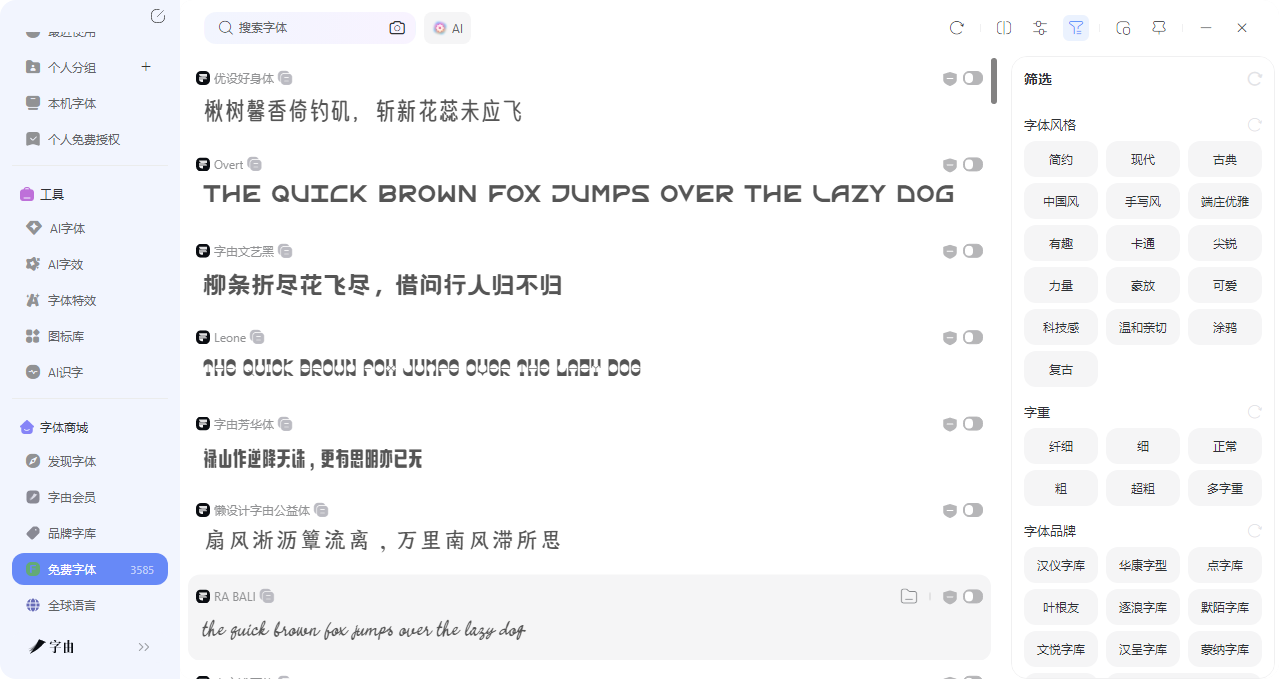
来字由,一键get小红书封面同款字体
小红书的流量密码其实有一半都藏在封面里,如果你是做日常的vlog 的话,灵动、可爱、活泼的字体应用在封面上会很吸睛;如果你是想发制作美食的视频,那么暖色调、有生活气息的字体会比较合适;又或者是你在做美妆博主,那么精致、漂亮的字体会很适配。那么说实在的,小红书不能包揽帖子的全部制作内容,当我们在另外一个平台制作的时候却没有办法使用小红书的字体,那么今天我将教大家如何在一款叫字由的字体平台里寻找小红书封面字体,我会按风格分类推荐一些适合做封面的字体,顺便把筛选方法也交代清楚。想做爆款帖子的朋友,直接收藏这篇。
1、关于字由
我先来讲一下为何要选择字由平台,是因为它收录了超过10500 款字体,其中3584 款是免费可商用的。这个体量意味着什么?就是你看到的大部分小红书封面字体,基本都能在这里翻到。不管是温柔的手写体、大气书法体,还是可爱的艺术字,字由里都有对应的选择。更重要的是,字由支持一键应用到PS、AI、Figma这些软件。你看中哪款字体,不用下载安装,在软件里点一下就能用。试错成本几乎为零——觉得不合适,换下一款接着试。
2、怎么在字由里找到适合的小红书的封面字体?
- 简约:适合极简风、干净利落的封面。
- 现代:适合时尚穿搭、美妆护肤类内容。干货分享这类内容,字体需要干净利落,不抢主体但又有质感,比如说字由文艺黑,既有黑体的稳重,又带一点手写感。用在“穿搭公式”“化妆技巧”“干货总结”上,高级又不死板。
- 古典:适合传统文化、国风类主题。
- 中国风:点进去全是书法体、楷体、隶书这类。这两年国风在小红书上特别火,二十四节气、传统节日、国潮穿搭,配上书法字体,格调瞬间拉高。比如说江西拙楷,带着朴拙手工感的楷书,不刻意追求工整,反而有味道。适合“立春”“中秋”“国风穿搭”这类主题。还有字由颜楷,颜真卿楷书风格,大气稳重。用在“书法”“传统文化”“中式美学”类封面上,压得住场子。
- 手写风:温柔手写、文艺范儿的字体都在这。这种字体在小红书上特别常见,用在情感文案、生活记录、读书笔记类封面上,都十分出效果。比如说字由芳华体,笔画柔和,带着手写的温度。适合“日常 plog ”“治愈系”“我的生活瞬间”这类封面。字体大小适中,排版起来很舒服。
- 端庄优雅:适合婚礼、纪念日、仪式感内容
- 有趣:活泼俏皮的字体,适合探店、美食类。
- 卡通:可爱萌系风格,适合母婴、萌宠。比如说点字婴宝,圆润可爱的风格,比婴宝更活泼一点。用在“美食打卡”“周末去哪儿”上,很有感染力。
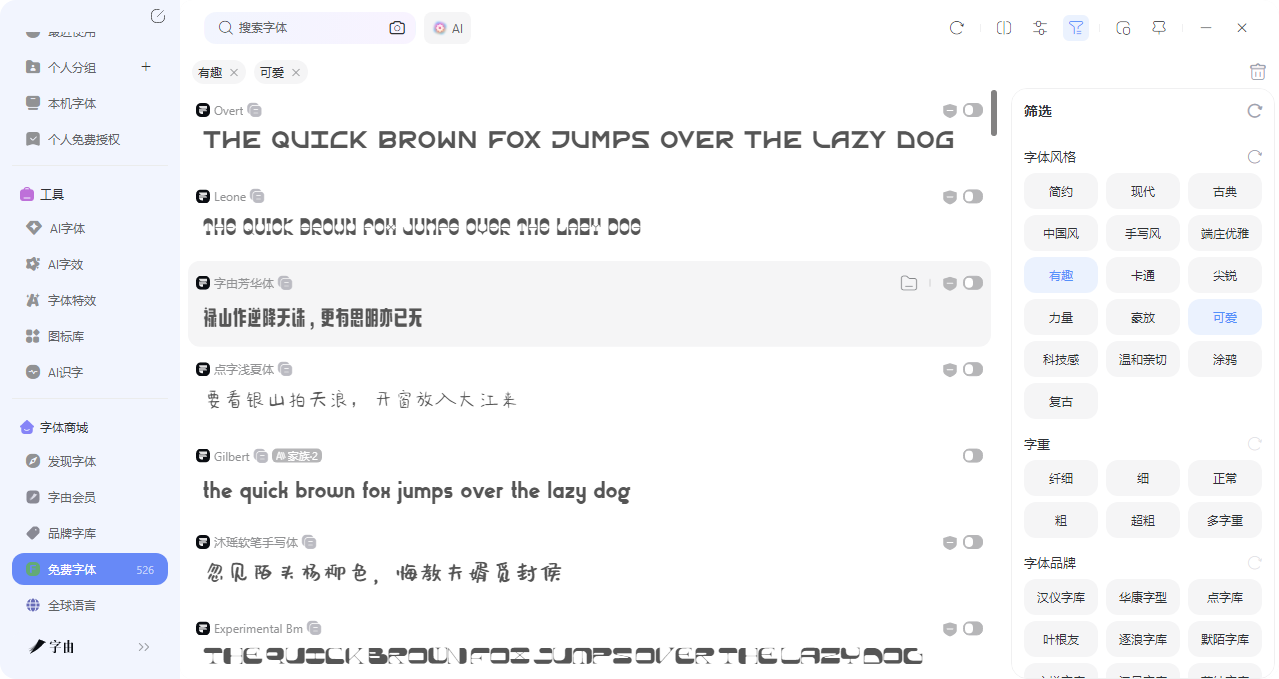
- 纤细/细:适合作为背景文字、小字点缀
- 正常:最常用的字重,正文标题都合适
- 粗/超粗:视觉冲击力强,适合做主标题,抓眼球
- 多字重:点进去可以看到字体家族,包含多个粗细版本,排版灵活性更高
3、除了常规字体库,还有品牌字体库做保
- 汉仪字库:国内知名字体厂商,品质稳定
- 华康字型:老牌字体公司,经典款多
- 点字库:字由自营字体,风格独特
- 叶根友:知名书法字体作者
- 蒙纳字库:国际大牌,Helvetica、Times New Roman都出自它家
- 文悦字库、汉呈字库、默陌字库等